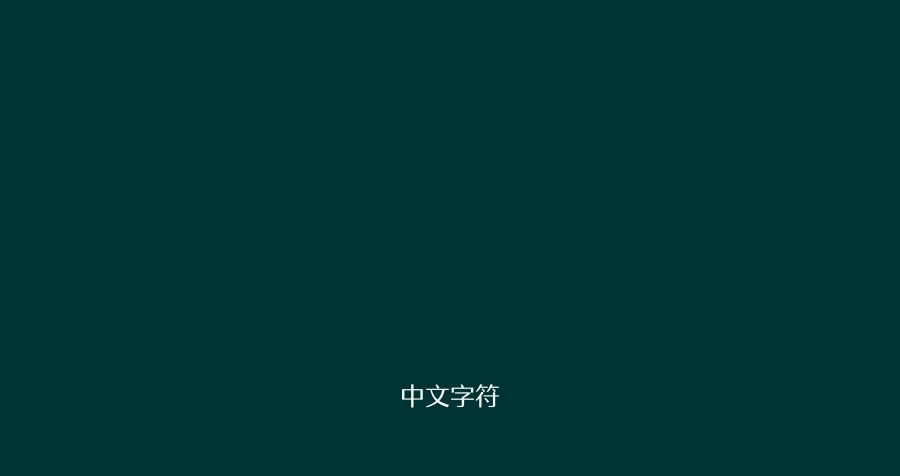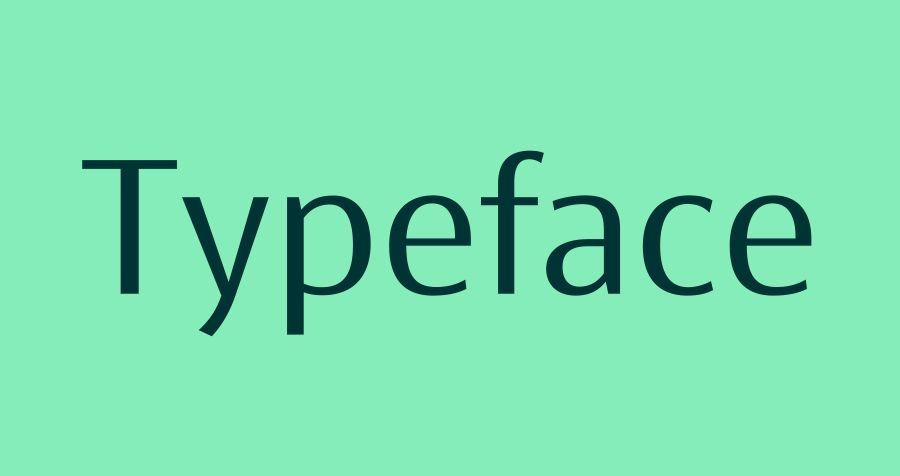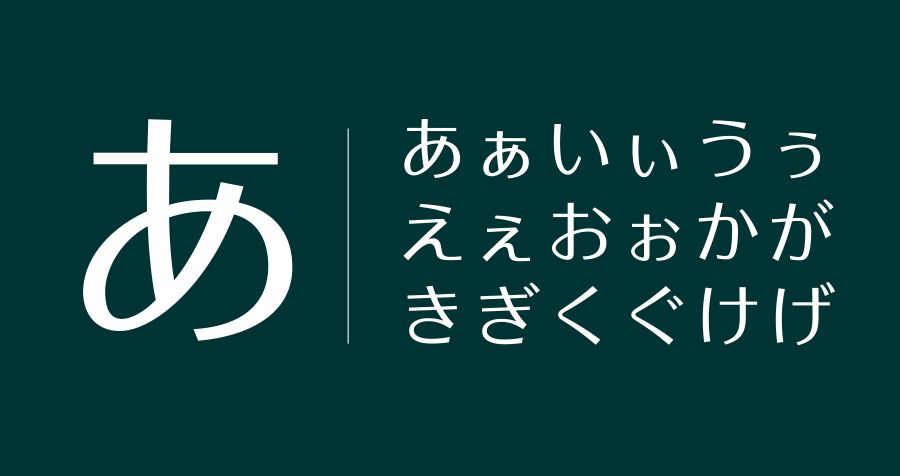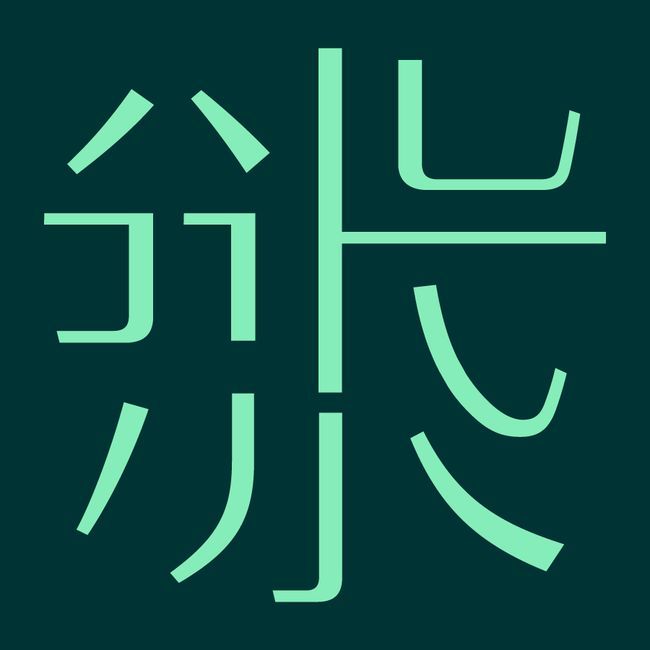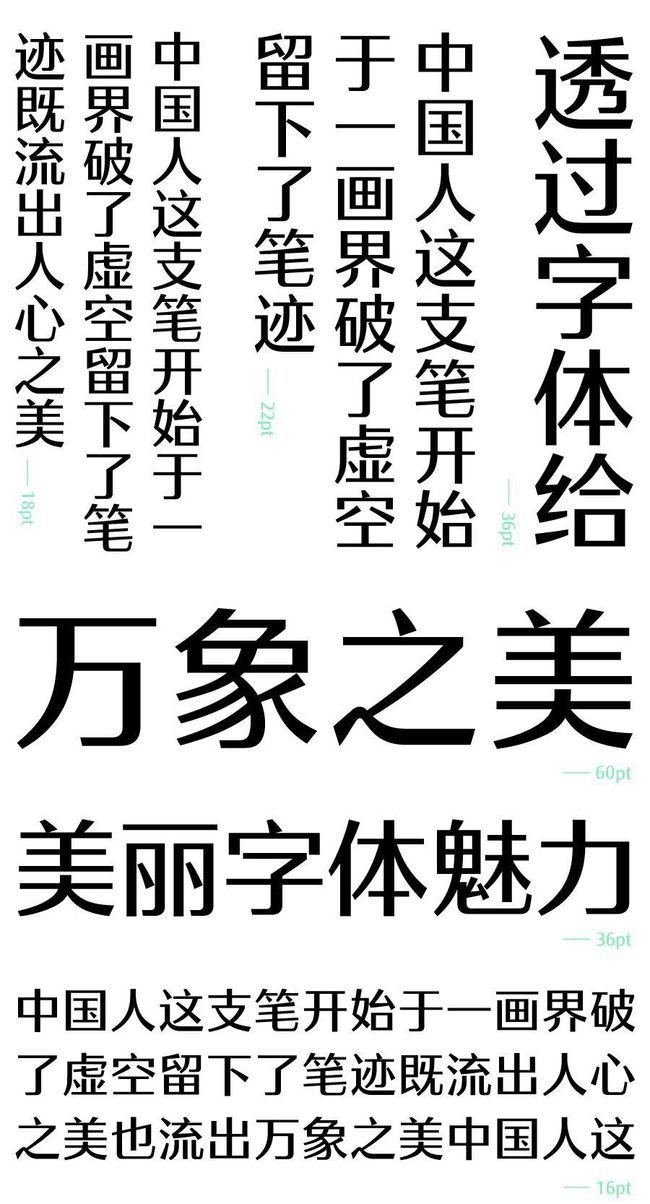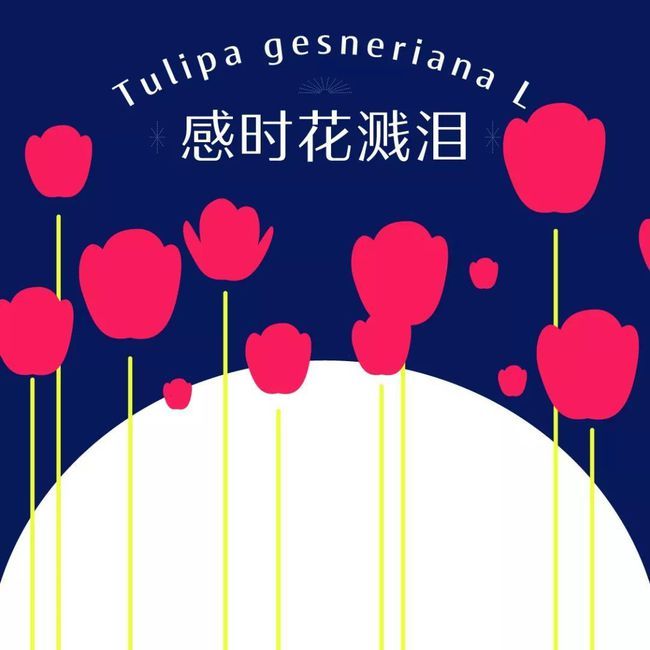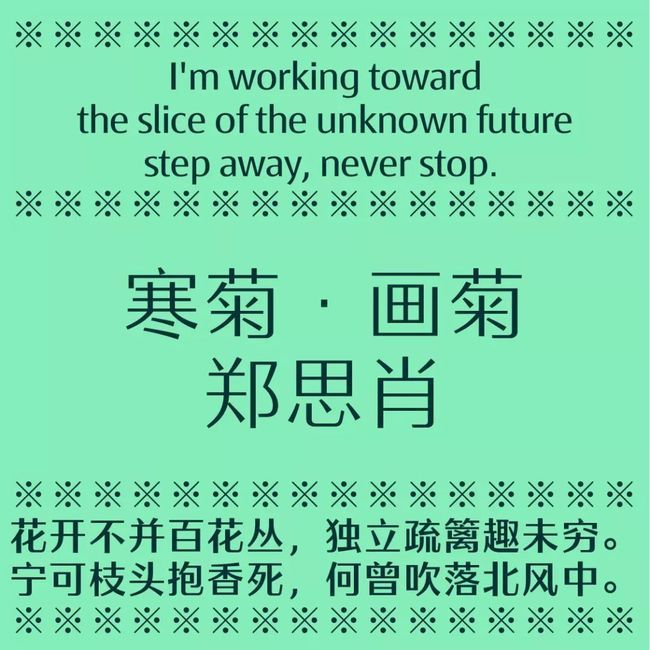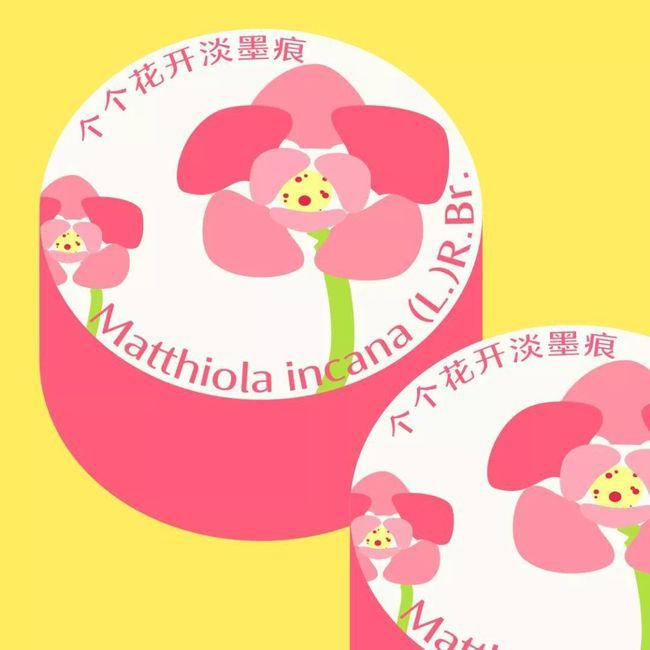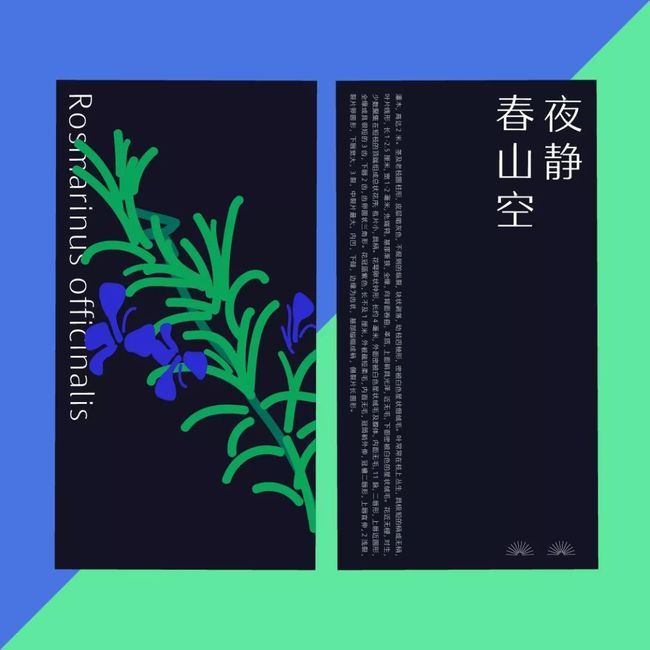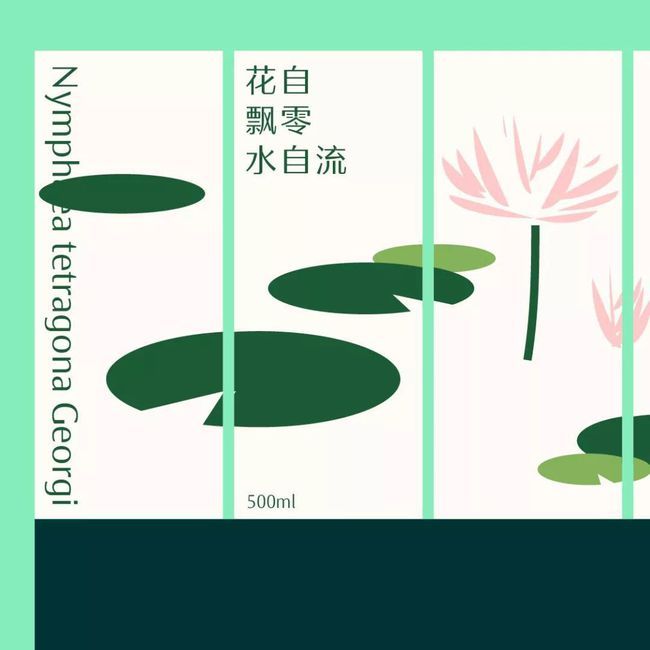
今天,方正字库发布了一款新字体--方正雅士黑。
方正雅士黑家族字体共有六个字重,能充分满足正文和标题的排版使用,是方正字库设计副总监汪文继榜书行之后又一力作。
设计源流
雅士黑设计开始于2012年,经过六年打磨,三易其稿,终于在2018年定型并形成字库。
雅士黑的创作灵感来源于经典的拉丁文字体Optima,这款大小写字母造型比例都具有古典气质的字体,给人一种优美的罗马字体感觉,发表五十多年来,至今还常在时尚行业被用来表现纤细与优雅。
在中文字体中,是否也能将衬线字体的优雅与无衬线字体的简洁融为一体?是否能将宋体与黑体优点完美合并?正是带着这种思考,汪文设计出了这款兼具复古与时尚、气质典雅的风格化黑体。
气质特征
方正雅士黑,既有黑体几何线条的硬朗,也有宋体笔画的粗细变化和优美弧线,做到了刚柔相济,优雅大方。
上图为雅士黑笔画风格,雅士黑家族包含6个字重,可以充分满足正文和标题的不同应用需求。
整套字库既有创新的时尚观感,又具备经典字体的稳重端庄。作为排版字体时,还能让阅读体验更加舒适,字里行间散发着中国的美学韵味。
增加英日文字符
此外,雅士黑的另一大特点则是,除了汉字部分之外,还设计了配套的拉丁字符和日文字符,方便使用者搭配使用。
拉丁字符吸收了Optima字体的特征,调整了字宽,更加现代和简洁。
日文字符造型严谨,中宫略宽,简洁而优美。
应用示例
方正雅士黑家族具有黑体和宋体的特征,它的适用场景也比较宽广:从手机等移动终端、电脑屏幕、纸质印刷,到户外广告等各类媒介都有良好表现。
感时花溅泪,恨别鸟惊心
花开不并百花丛,独立疏篱趣未穷
我家洗砚池头树,个个花开淡墨痕
人闲桂花落,夜静春山空
花自飘零水自流
待到山花烂漫时
犹有花枝俏
英文应用示范
日文应用示范
中英文风格对照